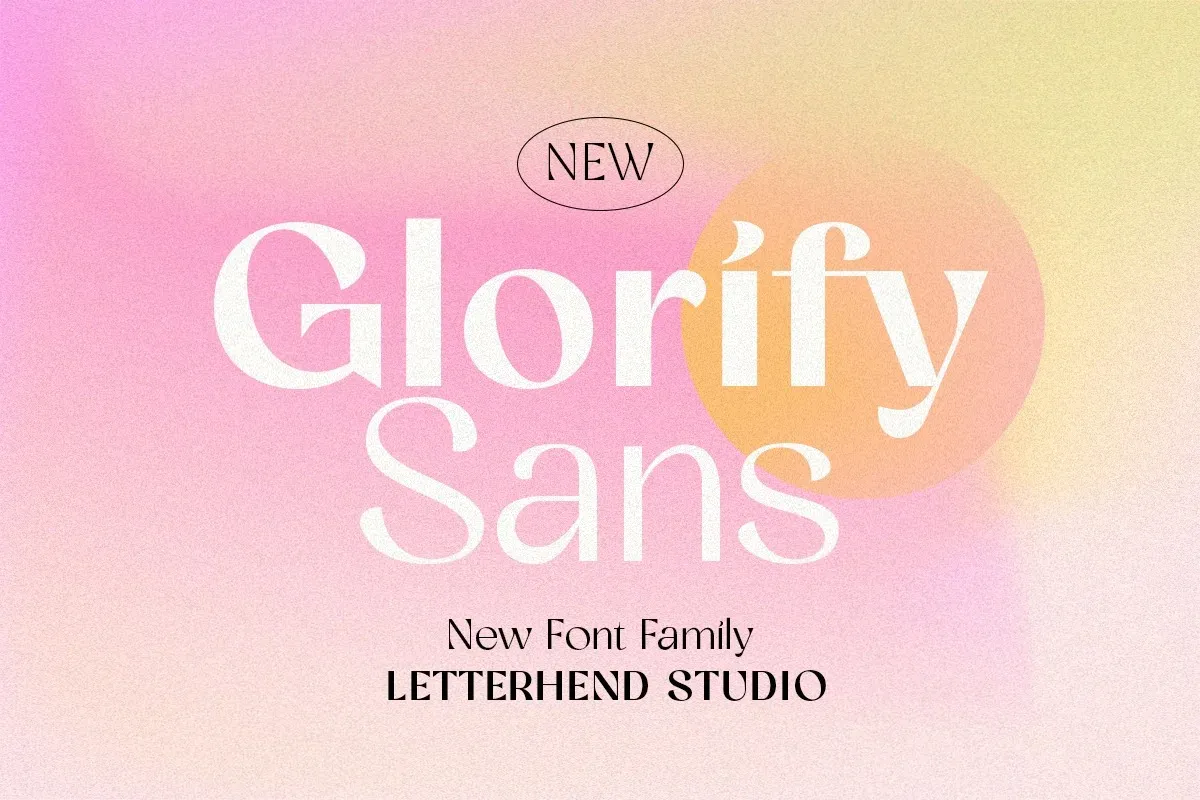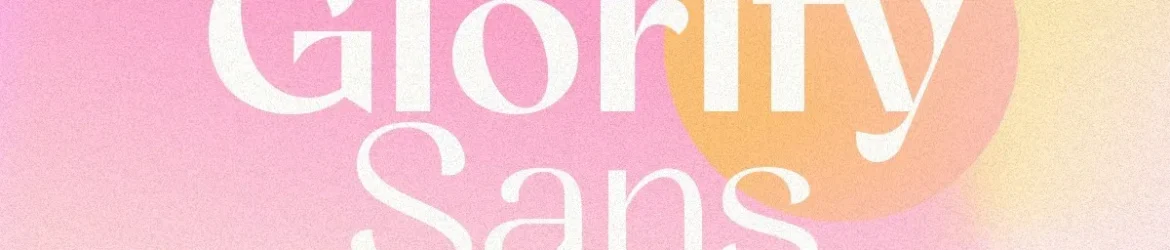
Glorify Sans Font – Download Grátis
A Glorify Sans é uma elegante tipografia sans serif que traz sutis contrastes, criada pelo designer Letterhend Studio. Ela oferece 8 estilos de peso diferentes para você personalizar e adaptar ao seu projeto, seja um headline chamativo ou até mesmo como uma tagline em cartazes, embalagens, livros, anúncios e mais. O formato único dos caracteres da Glorify Sans a torna única, permitindo que ela se destaque perfeitamente para os diferentes tipos de formas formais. Pode ser usada em invitações, rótulos, logotipos, revistas, livros, cartões de festas e moda, embalagens, cartões de lembrança, novelas ou etiquetas. Essa font é perfeita para quem procura uma tipografia com um ar contemporâneo que pode ser usada em vários formatos formais e não-formais. A Glorify Sans é uma ótima escolha se você busca um equilíbrio entre simplicidade e expressividade, proporcionando aos seus projetos a capacidade de destacar-se com elegância.